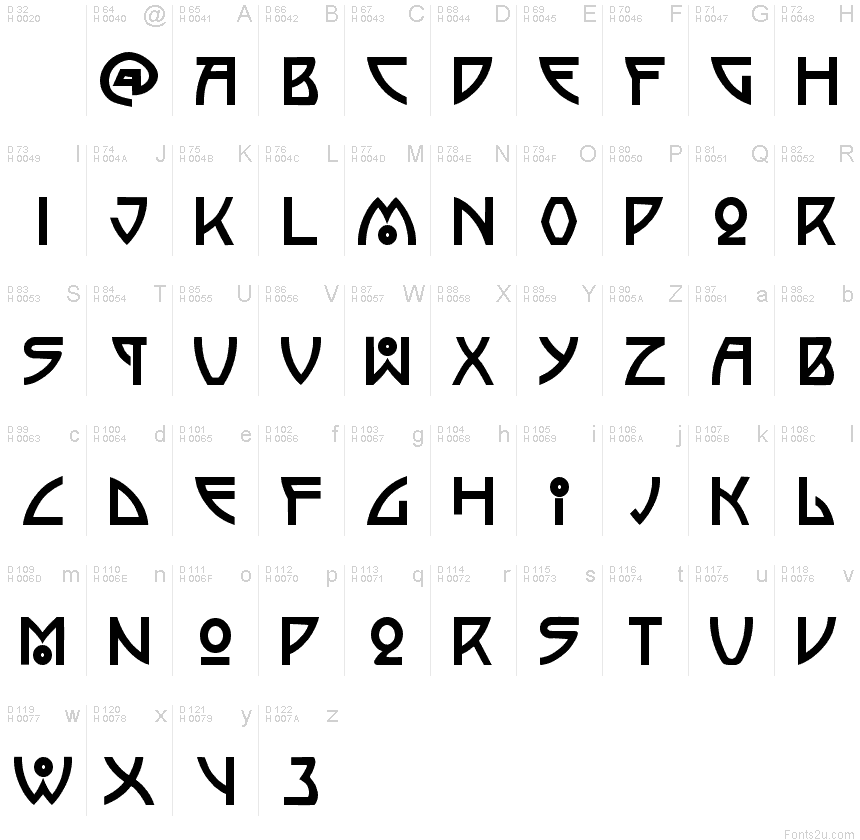
Semiramis, darmowy geometryczny krój wyświetlaczowy w stylu retro od Davida F. Nalle’a, nawiązuje do estetyki art déco i futuryzmu. Litery wyglądają, jakby zostały wyrzeźbione z szerokich łuków i ostrych przekątnych. Rytm pisma wynika z zestawienia zaokrąglonych rogów z ostrymi łączeniami i charakterystycznymi okrągłymi kropkami, co nadaje mu opływowy, niemal emblematyczny charakter, odróżniający go od typowych krojów nagłówkowych.
Dzięki temu świetnie sprawdzi się na plakatach, okładkach albumów, w menu koktajlowych, przy brandingu butików i w napisach początkowych – wszędzie tam, gdzie darmowy font ma łączyć w sobie ozdobność i wyrazisty charakter. Sprawdza się również w krótkich tekstach lub monogramach, ponieważ litery szybko układają się w śmiałe, graficzne kształty.